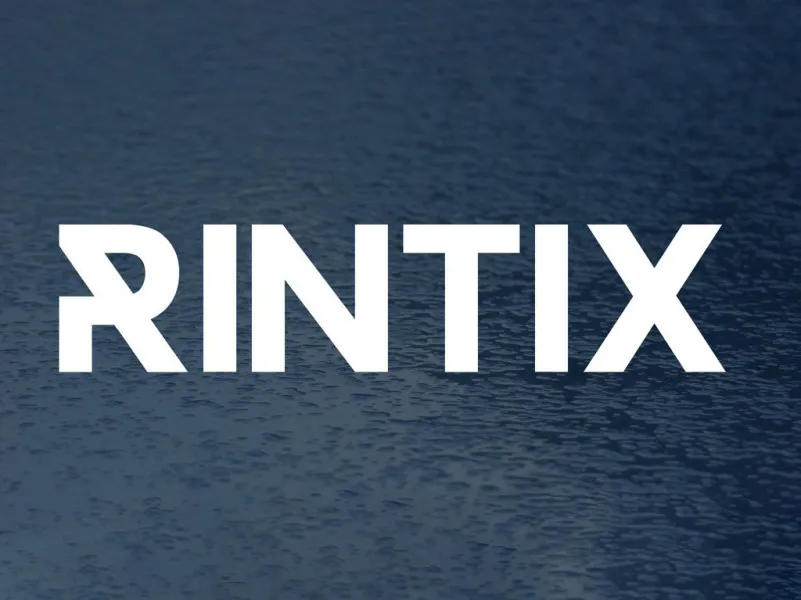
A Rintix Font é uma tipografia sans-serif que traz estilo moderno para qualquer projeto. Inspirada no mundo industrial, ela carrega uma elegância única sob seu design masculino e firme, proporcionando um resultado final sofisticado e contemporâneo. Esta fonte é perfeita para utilização em diversas aplicações, desde cartazes até projetos de negócios, mantendo sempre o brilho necessário para destacar seu trabalho. A Rintix atinge uma harmonia entre clareza e luxúria, tornando-a ideal tanto para elementos visuais como textos informativos, garantindo que seja utilizada com frequência por designers em sua paleta de ferramentas. Combinada a outras fontes ou aplicada sozinha, essa tipografia sem serif é uma escolha inteligente e inovadora para qualquer projeto visual contemporâneo.